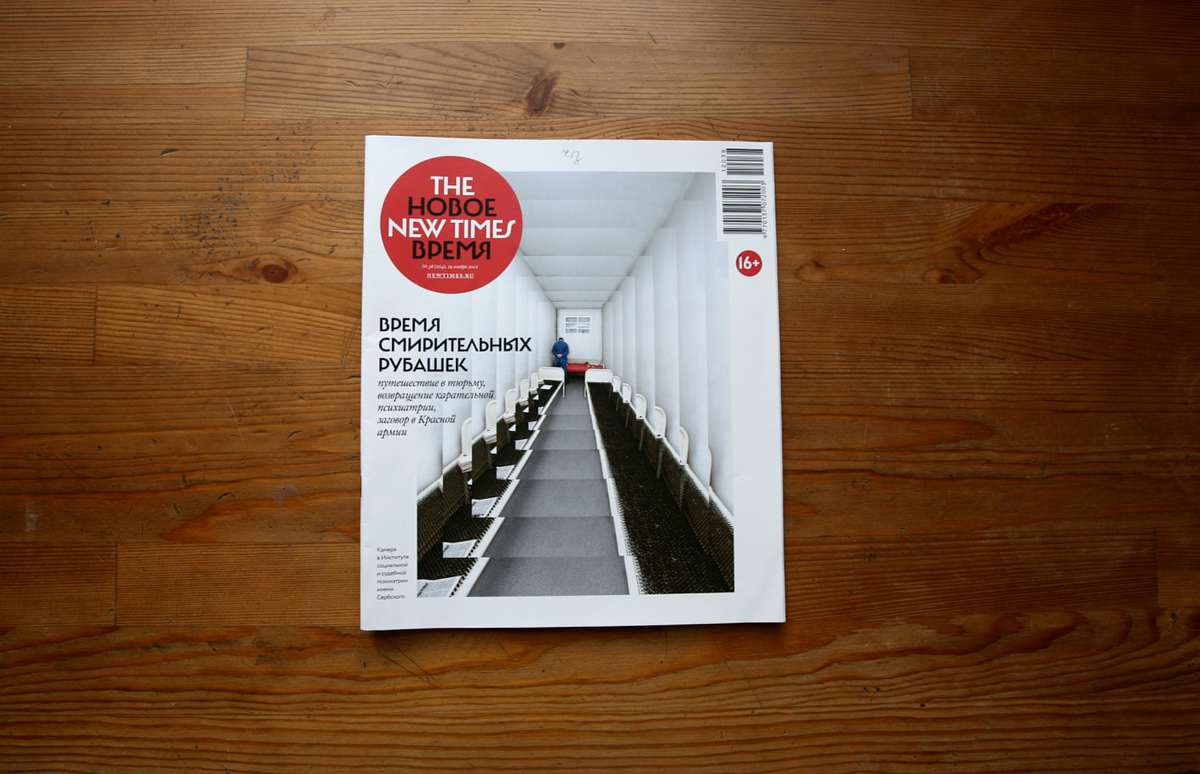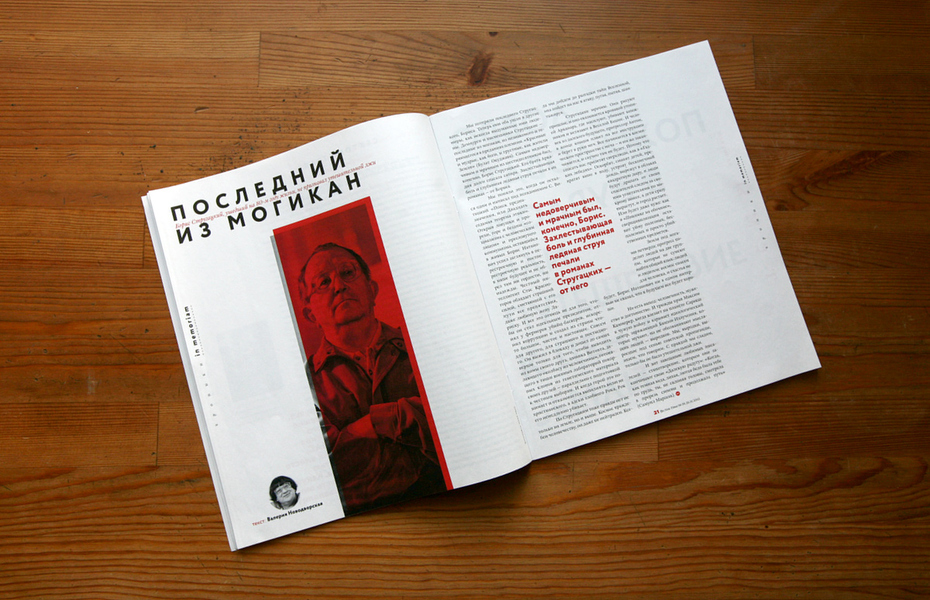
The New Times
Жур­нал The New Times ед­ва ли мож­но счи­тать на­след­ни­ком со­вет­ско­го «Но­во­го вре­ме­ни», по­ли­ти­че­ско­го еже­не­дель­ни­ка, ко­то­рый вы­хо­дил с 1943 го­да в Моск­ве и осве­щал вну­трен­нее и меж­ду­на­род­ное по­ло­же­ние стра­ны. Ак­ту­аль­ная вер­сия вы­пус­ка­ет­ся с 2007 го­да из­да­те­лем Ире­ной Лес­нев­ской в со­ю­зе с глав­ным ре­дак­то­ром Ев­ге­ни­ей Аль­бац. В 2008 го­ду жю­ри ев­ро­пей­ской пре­мии «Сво­бод­ная прес­са Вос­точ­ной Ев­ро­пы» от­ме­ти­ло The New Times как од­но из луч­ших пе­чат­ных из­да­ний в Рос­сии, от­ли­ча­ю­ще­е­ся «сво­бод­ным со­зна­ни­ем и мне­ни­ем». О ре­ди­зай­не, устрой­стве жур­на­ла и ис­пан­ской ре­во­лю­ции рас­ска­зал Юрий Остро­менц­кий, ав­тор но­во­го ма­ке­та.
же­не­дель­ный труд ре­дак­ции жур­на­ла The New Times уме­ща­ет­ся на 64-х по­ло­сах, пре­иму­ще­ствен­но в двух­ко­лон­ни­ке, ак­тив­но при­прав­лен­ном крас­ны­ми ак­цен­та­ми вре­зов, ли­дов и ци­тат. Мно­гие ма­те­ри­а­лы не рас­по­ла­га­ют к бег­ло­му чте­нию, тре­буя от чи­та­те­ля на­ме­ре­ния, а за­тем и уси­лия для по­гру­же­ния в текст. Свое­об­раз­ный при­вет пе­ре­да­ют чи­та­те­лю в кон­це но­ме­ров Брод­ский, Вы­соц­кий, Га­лич, Гре­бен­щи­ков, Ле­тов и дру­гие, чьи сти­хи и го­ло­са сли­ва­ют­ся в гимн гра­ждан­ско­го и че­ло­ве­че­ско­го ду­ха. Как дол­жен вы­гля­деть об­ще­ствен­но-по­ли­ти­че­ский жур­нал, ка­ким об­ра­зом вы­стро­ить раз­во­ро­ты, ка­кую роль от­ве­сти изоб­ра­же­ни­ям и, на­ко­нец, ка­кая ин­то­на­ция долж­на быть у за­го­лов­ков и тек­стов — во­про­сы, на ко­то­рые ди­зай­нер даёт от­ве­ты в сво­ей ра­бо­те.
Жур­нал The New Times — од­но из не­мно­гих здрав­ству­ю­щих се­го­дня из­да­ний дей­стви­тель­но ли­бе­раль­но­го ха­рак­те­ра. Что вы счи­та­ли важ­ным для се­бя, участ­вуя в его раз­ра­бот­ке?
Для ме­ня бы­ло важ­ным то, что, ко­гда я за­ни­мал­ся жур­на­лом, он пол­но­стью со­от­вет­ство­вал мо­е­му пред­став­ле­нию о ду­хе вре­ме­ни. Мы с Фи­лип­пом Дзяд­ко, быв­шим ре­дак­то­ром «Боль­шо­го Го­ро­да», бы­ли при­гла­ше­ны об­но­вить жур­нал. Я на­ри­со­вал ма­кет, по­мог его за­пу­стить и с фе­вра­ля не имею от­но­ше­ния к вы­пус­ку те­ку­щих но­ме­ров. Сей­час там за глав­но­го ди­зай­нер Иван Сте­па­нен­ко.
The New Times и «Боль­шой Го­род» — жур­на­лы до­воль­но раз­ные, так же как и их ауди­то­рии. Как бы­стро вы на­шли и по­чув­ство­ва­ли тот ви­зу­аль­ный язык, ко­то­рый ну­жен но­во­му из­да­нию? Сколь­ко вре­ме­ни ушло на ре­ди­зайн?
К мо­мен­ту на­ше­го с Фи­лип­пом ухо­да из «Боль­шо­го Го­ро­да» мы бы­ли близ­ки к же­ла­нию схва­тить­ся за бу­лыж­ник, а в The New Times он как раз ле­жал. Так что всё про­ис­хо­ди­ло очень ор­га­нич­но и во­вре­мя. На ре­ди­зайн ушло, ка­жет­ся, ме­ся­ца два. Фи­зи­че­ские га­ба­ри­ты из­да­ния оста­лись преж­ни­ми — ра­бо­та шла вну­три. Пе­ред на­ми бы­ла по­став­ле­на про­стая за­да­ча — об­но­вить жур­нал. Сде­лать его удоб­нее для чи­та­те­ля и для ре­дак­ции и сде­лать так, что­бы он раз­го­ва­ри­вал се­го­дняш­ним язы­ком. Ви­ди­мо, наш уход из «Боль­шо­го Го­ро­да» сов­пал с же­ла­ни­ем глав­но­го ре­дак­то­ра Ев­ге­нии Аль­бац при­вне­сти в NT как раз то, что мы с Фи­лип­пом уме­ем. Бо­нус — ду­хо­вые ор­ке­стры в ре­дак­ции по празд­ни­кам.
Об­раз жур­на­ла в силь­ной сте­пе­ни фор­ми­ру­ет его ак­ци­дент­ный шрифт Carmela. На­пра­ши­ва­ет­ся не­ко­то­рая ана­ло­гия с за­го­ло­воч­ным шриф­том жур­на­ла New Yorker (шрифт Irvin Type, ав­тор Rea Irvin, 1925): есть об­щая ма­нер­ность в пла­сти­че­ских эле­мен­тах и не­ко­то­рых де­та­лях. Он раз­ра­бо­тан спе­ци­аль­но для жур­на­ла?
Ду­маю, вы счи­та­е­те воз­мож­ным их срав­ни­вать из-за то­го, что ви­ди­те у них при­мер­но од­ни и те же вре­мен­ные кор­ни. Оба эти шриф­та так или ина­че за­вя­за­ны на эсте­ти­ке мо­дер­на. В моём слу­чае на ис­пан­ской гра­фи­ке ре­во­лю­ци­он­ных 30-х. А у неё но­ги рас­тут как раз та­ки из мо­дер­на.
В 2011–2012 го­дах ме­ня пёр­ло от ис­пан­ско­го пла­ка­та времён Гра­ждан­ской вой­ны. У ме­ня бы­ло ощу­ще­ние, что это со­впaда­ет с тем, что но­сит­ся в воз­ду­хе. Cвои мыс­ли я на­чал за­со­вы­вать в «Боль­шой Го­род», сде­лал па­ру шриф­тов, а уй­дя из не­го, на­чал ри­со­вать Кар­ме­лу. Ко­гда я ри­со­вал его, ду­мал о том, что важ­но не сде­лать сти­ли­за­цию ре­во­лю­ци­он­ной гра­фи­ки, а, обер­нув­шись по­чти на сто лет на­зад, про­пу­стив че­рез се­бя и огля­нув­шись во­круг, рас­ска­зать что-то се­го­дняш­нее, что-то, что у ме­ня на кон­чи­ках паль­цев. Нас с Фи­лип­пом по­зва­ли как ко­ман­ду с уже сло­жив­шей­ся ин­то­на­ци­ей, и мы про­сто про­дол­жа­ли го­во­рить так, как мы уме­ли. И то, что мы хо­те­ли рас­ска­зать в NT, ста­ло удоб­но рас­ска­зы­вать Кар­ме­лой. Так он стал го­ло­сом The New Times. Кста­ти, у шриф­та есть ещё два сти­ли­сти­че­ских се­та, ко­то­рые не ис­поль­зу­ют­ся в жур­на­ле, а сам шрифт всё ещё на­хо­дит­ся в ра­бо­те. А на­зы­ва­ет­ся он так, по­то­му что…
Himnos y Canciones de la Guerra Civil Española — España 1936–1939. Coro Popular Jabalón
С че­го на­чи­на­ет­ся ра­бо­та над ма­ке­том? Ко­гда по­яв­ля­ет­ся по­ни­ма­ние основ­ной ин­то­на­ции, на­бор­ной па­ры и клю­че­вых шриф­тов?
Я не­ко­то­рое вре­мя че­шу ре­пу, смот­рю по сто­ро­нам, на го­ри­зонт, а по­том са­жусь, ри­сую на­бро­сок ма­ке­та, по­том счи­таю сет­ку, и всё вол­шеб­ным об­ра­зом по­чти все­гда иде­аль­но с ней сов­па­да­ет. Это, ра­зу­ме­ет­ся, амо­раль­но. Пе­ре­дел­ки для ме­ня — са­мое му­чи­тель­ное, не­при­ят­ное, слож­ное и так да­лее. Ка­жет­ся, я до­воль­но бы­стро ра­бо­таю, ин­то­на­ция по­яв­ля­ет­ся са­ма со­бой, так же как и в раз­го­во­ре — ли­бо у те­бя по­лу­ча­ет­ся раз­го­ва­ри­вать с че­ло­ве­ком, ли­бо до сви­да­ния. По­это­му William был вы­бран сра­зу и сра­зу иде­аль­но встал. На кон­тра­сте с Circe и Carmela, как и за­ду­мы­ва­лось.
Сло­ва уров­ня «об­раз» и «кон­цеп­ция» по­яв­ля­ют­ся поз­же, при не­об­хо­ди­мо­сти. Ли­бо ск­ла­ды­ва­ет­ся лег­ко и сра­зу, ли­бо по­том нуж­но дол­го что-то до­пи­ли­вать и до­уточ­нять, но то­гда ни «об­раз», ни «кон­цеп­ция» не по­мо­гут.
По­лу­ча­ет­ся, в ма­ке­те ра­бо­та­ют сра­зу три шриф­та уче­ни­ков Алек­сан­дра Тар­бе­е­ва — ваш (Carmela), William Ма­ши До­ре­ули в на­бо­ре и Circe Са­ши Ко­роль­ко­вой «су­флёром» и в за­го­лов­ках. Это сов­па­де­ние?
На­вер­ное. А хо­тя нет. На­сколь­ко я мо­гу су­дить, сей­час всё са­мое све­жее и при этом ра­бо­то­спо­соб­ное ис­хо­дит в основ­ном от уче­ни­ков Тар­бе­е­ва. Это если смот­реть на мо­ло­дых, ра­зу­ме­ет­ся.
«Де­лай каж­дый но­мер как по­след­ний» — од­на из ва­ших «за­по­ве­дей» (В об­зо­ре на Colta.ru — Прим. ред.). По­лу­ча­лось? Ка­кие из но­ме­ров, об­ло­жек или раз­во­ро­тов вы мог­ли бы от­ме­тить?
В The New Times каж­дый но­мер ка­жет­ся по­след­ним в го­раз­до боль­шей сте­пе­ни, чем это мог­ло ка­зать­ся в «Боль­шом Го­ро­де», по по­нят­ным при­чи­нам. Об­лож­ки и раз­во­ро­ты при­ла­га­ют­ся.